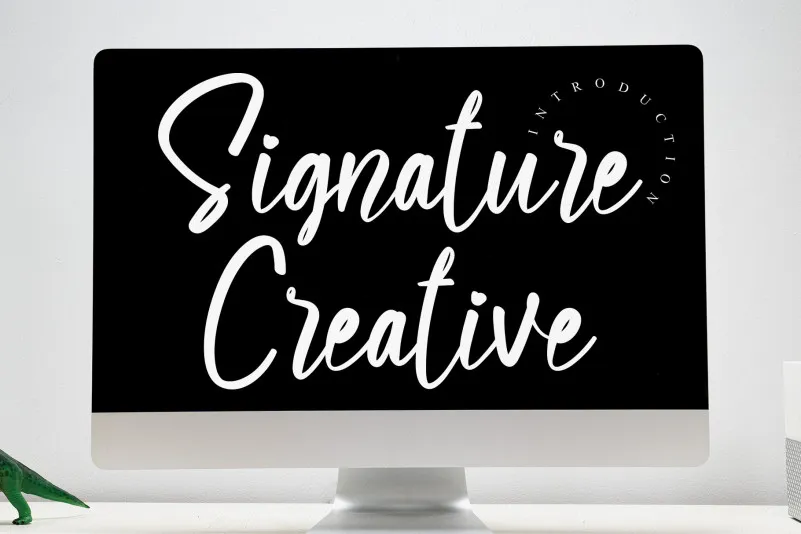
Signature Creative Script Font – Download Grátis
A fonte Signature Creative Script é uma criação especial do designer creativeletter para quem aprecia a arte fluida e envolvente que vem ao encontro dos sentimentos e ideias mais vivos de cada escritor. Embora não possamos descrever os detalhes físicos da fonte, como o tamanho ou cor exatos, podemos dizer que ela é perfeita para quem busca expressar um toque pessoal em seu trabalho. Através dos movimentos elegantes e delicados dessa script criativa, o usuário pode transmitir sua essência de maneira única e profunda. Seja uma carta de amor escrita à mão ou uma breve declaração em um poster, a Signature Creative Script traz vida ao texto, transformando simples palavras em obras de arte. Com seu design fluido que flui semelhante às letras manuscritas da pessoa mais confiante e criativa, essa fonte é a escolha perfeita para quem busca expressar suas ideias de maneira única. Seja você um artista plástico desenhando uma obra de arte ou um designer gráfico adicionando um toque distintivo em seu trabalho, a Signature Creative Script estará sempre à mão para ajudá-lo a trazer seus pensamentos e emoções ao papel de uma maneira singular e profunda.